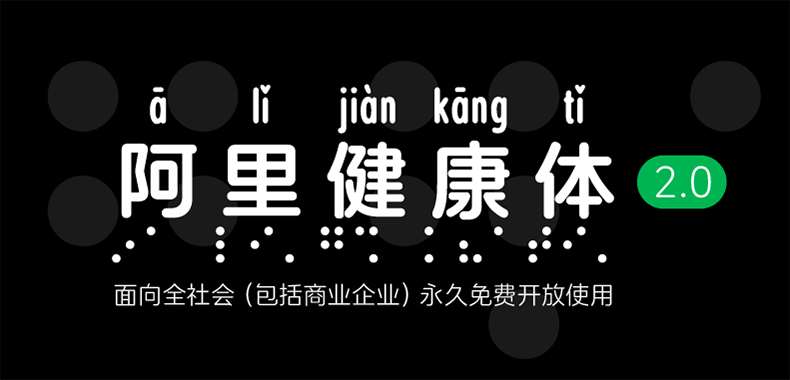
阿里健康体
阿里健康体,这款字体结构工整、笔画清晰,兼顾美观与易读性,适用于标题、正文、海报、包装、LOGO 等多种场景。字形优雅稳定,风格百搭耐看,适配日常排版与创意设计,让文字呈现更舒适、更具质感。阿里健康体一笔一画,皆是细节,以均衡的比例、流畅的线条打造舒适视觉体验,字形端正大气,风格简约现代。无论是商业设计、品牌宣传还是日常排版,都能轻松驾驭,让文字更有格调与力量。阿里健康体字体下载。
2023年11月,由阿里健康设计与方正字库共同设计开发的阿里健康体2.0家族字体正式发布。该字体以无障碍设计为初衷,以服务于视障人士为目标,是首款中文盲文注音定制字体。为了鼓励更多人关注无障碍设计,进一步推进医疗健康服务的普惠可及,阿里健康体2.0面向全社会(包括商业企业)永久免费开放使用,希望通过技术公益,推动无障碍环境建设,传递现代设计的人文关怀。
基于阿里健康有温度的关怀感的品牌定位,以及为了保持更好的文化承接性,在原始标志字体圆体风格的基础上,设计师统一了笔画特征,使字体更加规范和谐。笔画多以几何化处理方式,让字形看上去更加严谨端庄,符合阿里健康医疗行业的品牌属性。阿里健康体广泛应用于品牌文化展示、广告宣传以及物料印刷等整套视觉系统中。
此款字体是国内首款服务于视障人士的中文盲文注音定制字体,解决药品及产品包装上盲文、生僻字使用问题,为视障人士搭建一座沟通世界的桥梁。笔画多以几何化处理方式,让字形看上去更加亲和有温度。
针对药品名生僻字认读障碍问题,以及关注弱势群体用药问题,本次阿里健康体添加了注音字库和盲文注音字库,以方便药品生产各个环节参考应用,同时呼吁社会关注弱势群体,为他们送去关怀与温暖。